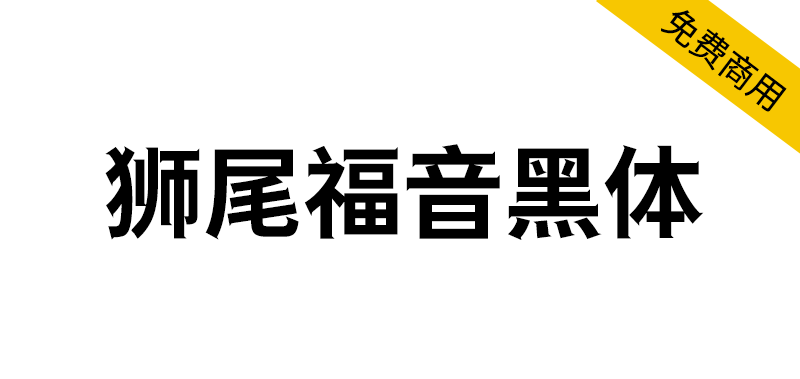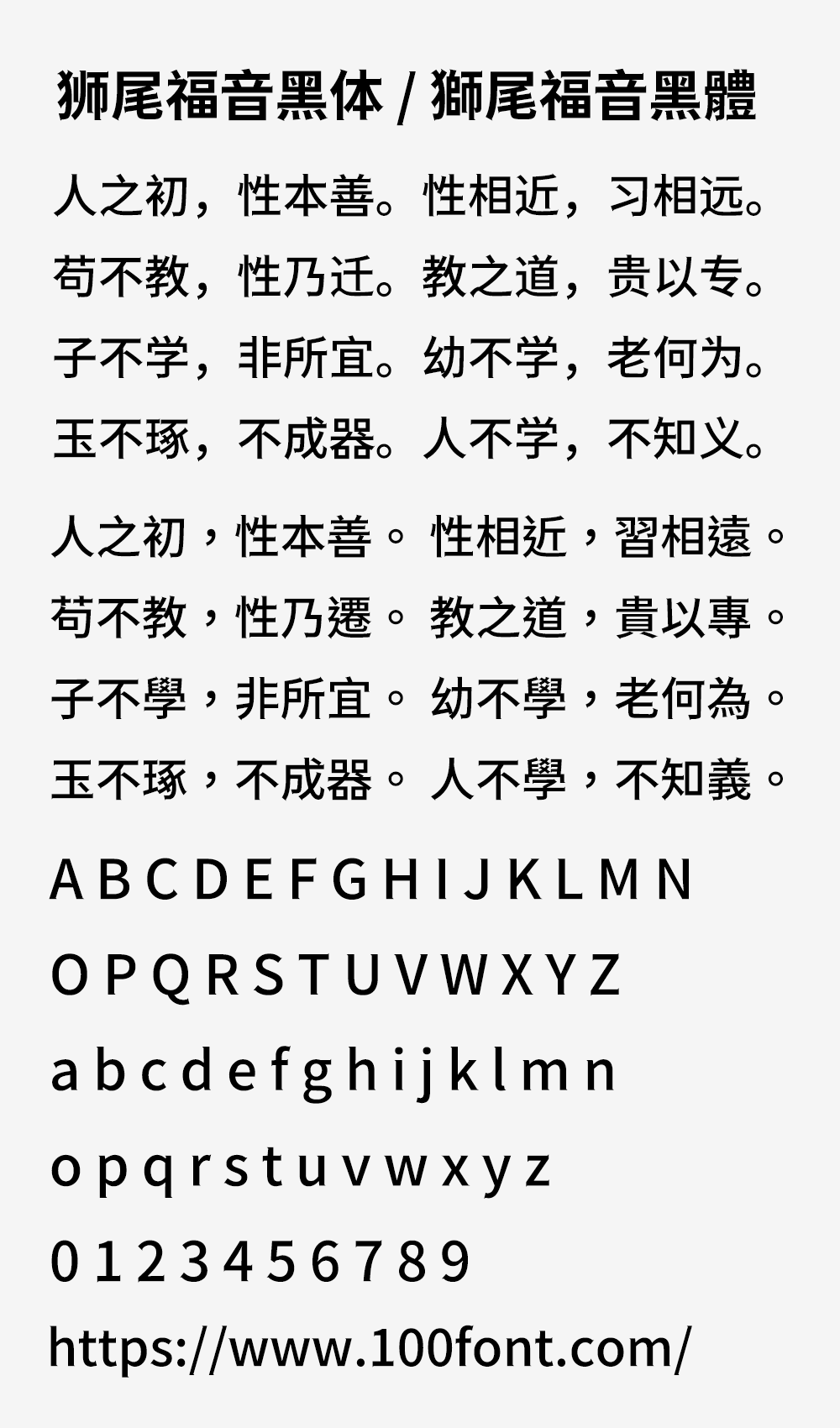
狮尾福音黑体基于思源黑体的笔触增加三角形和拔脚改造,更加简明现代化的字体。狮尾福音黑体的特色是「一」字的开头和结尾笔触由平头增加一个小小的三角形。和思源黑体一样,有7种字重,支持简体中文、繁体中文、韩文与日文,可以免费商用,欢迎大家自由应用、自由优化、自由改作!
狮尾福音黑体与「狮尾福腿黑体」差别在有没有拔脚,「拔脚」就是会有较少的笔画,例如移除「口」字的左右下角会多出的短线条。有拔脚的字会较圆,但是会造成有些字因直接去掉腿后左右不平衡、左右不对衬的「悬空」问题。改使用「腿」系列字体就不会有这个问题。